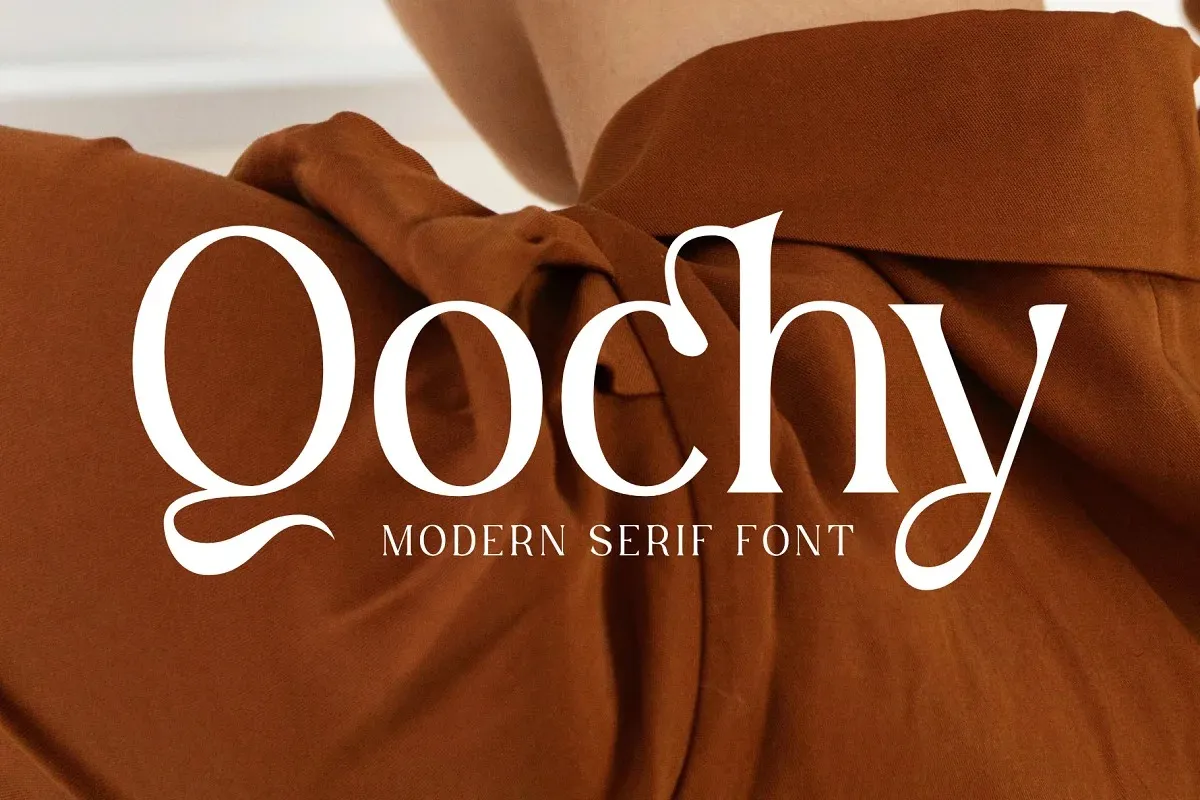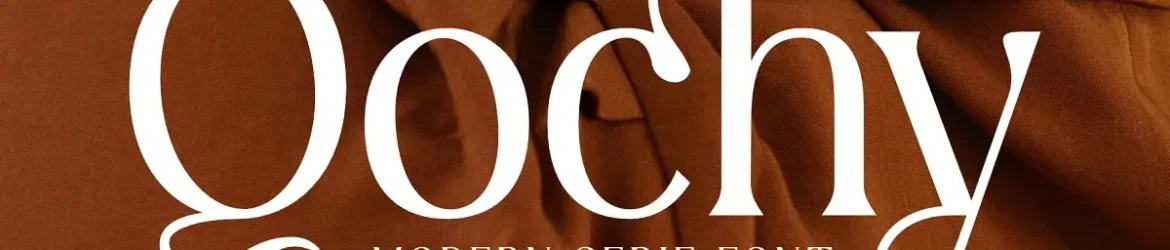
A Qochy Font é uma serifada moderna e elegante criada pela Prioritype, disponível para download por meio do site 99designs. Esta fonte se destaca por suas curvas suaves e detalhes aprimorados que garantem um visual moderno com o toque de serifas clássico. Com seu design clean e forte, ela é perfeita para aplicativos em estilos como moda e editoriais, onde busca-se uma harmonia entre antiguidade e contemporaneidade. A Qochy seria ideal para criações de logotipos, marcasuramentos, capas de magazines, páginas de início da web ou postagens no Instagram, oferecendo uma combinação única de modernidade e elegância que se adequa perfeitamente a diversas necessidades de design.